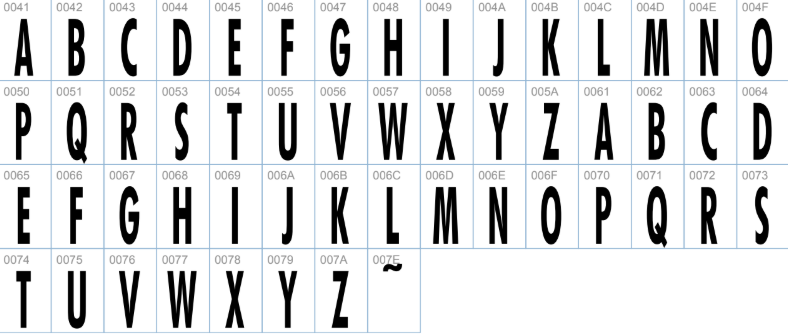
A identidade visual do Red Bull Bragantino é, sem dúvida, uma das mais modernas e arrojadas do futebol brasileiro. Alinhada com a estética global da marca Red Bull, a tipografia usada nos uniformes do “Massa Bruta” é sempre um destaque. Para a temporada 2024-2025, os kits desenvolvidos pela New Balance trazem uma fonte que combina energia, velocidade e uma legibilidade impecável, refletindo o estilo de jogo da equipe.
Estilo Visual: Energia e Precisão
A fonte da temporada 2024-2025 do Red Bull Bragantino é marcada por sua construção geométrica e cortes angulares. Ela transmite uma sensação de movimento e precisão tecnológica, características intrínsecas à marca Red Bull.
Diferente de fontes mais tradicionais, ela possui um design “condensado” (mais estreito), que permite que nomes longos se ajustem bem nas costas das camisas, mantendo uma excelente leitura à distância. Os ângulos agudos, especialmente visíveis em números como o “4” ou o “7”, dão a ela uma identidade única e instantaneamente reconhecível, vista em todos os uniformes (principal, reserva e alternativo) assinados pela New Balance nesta temporada.